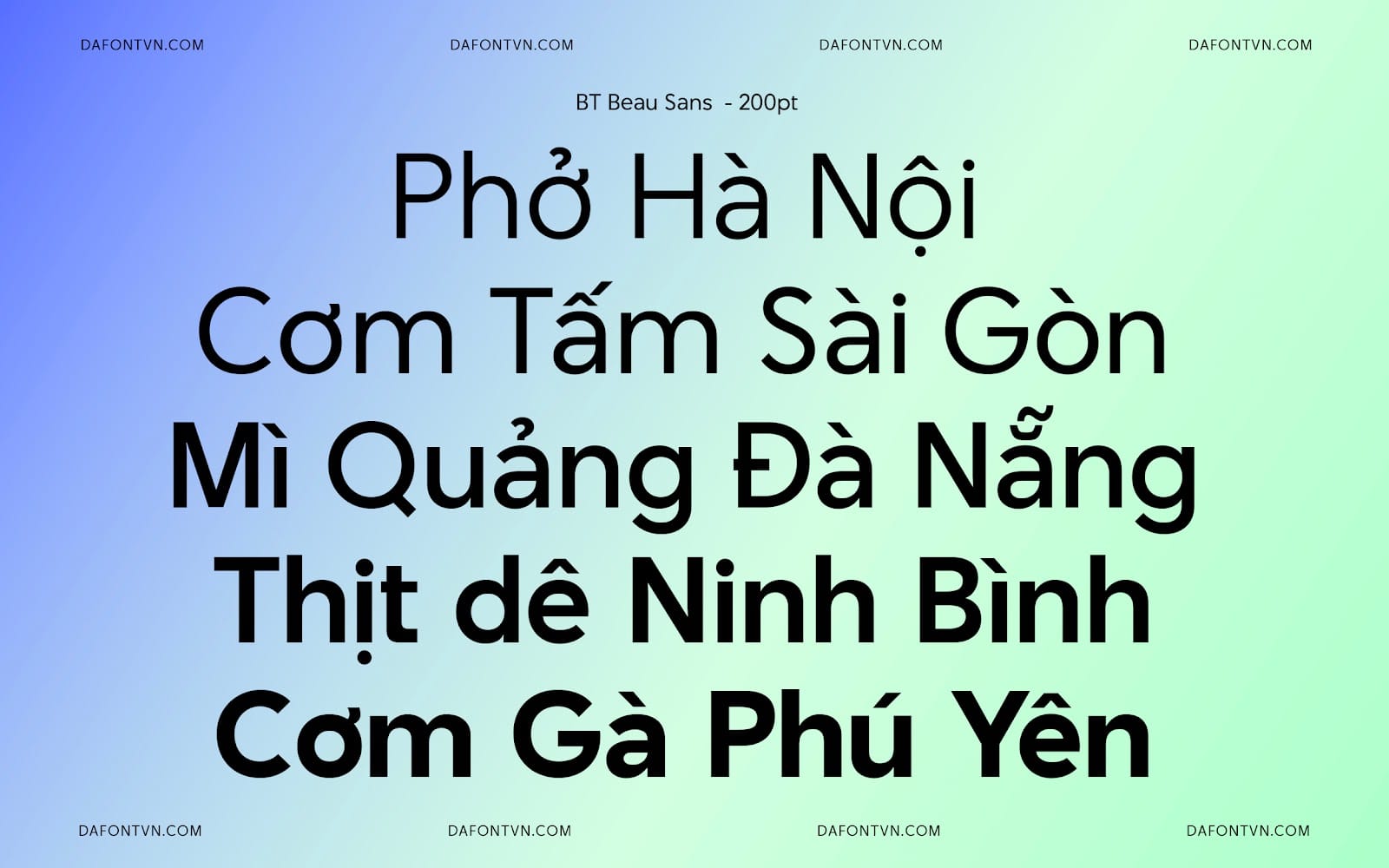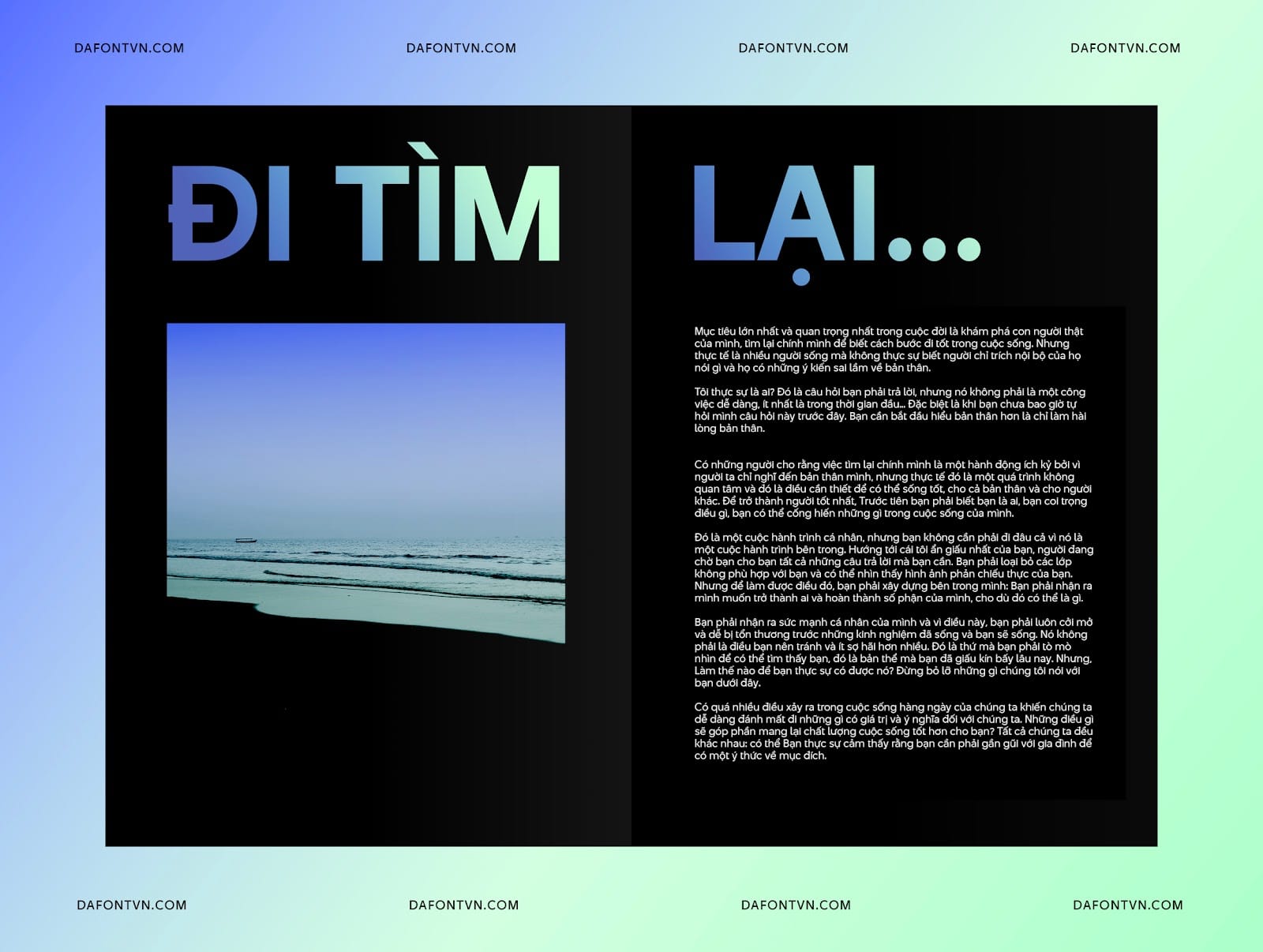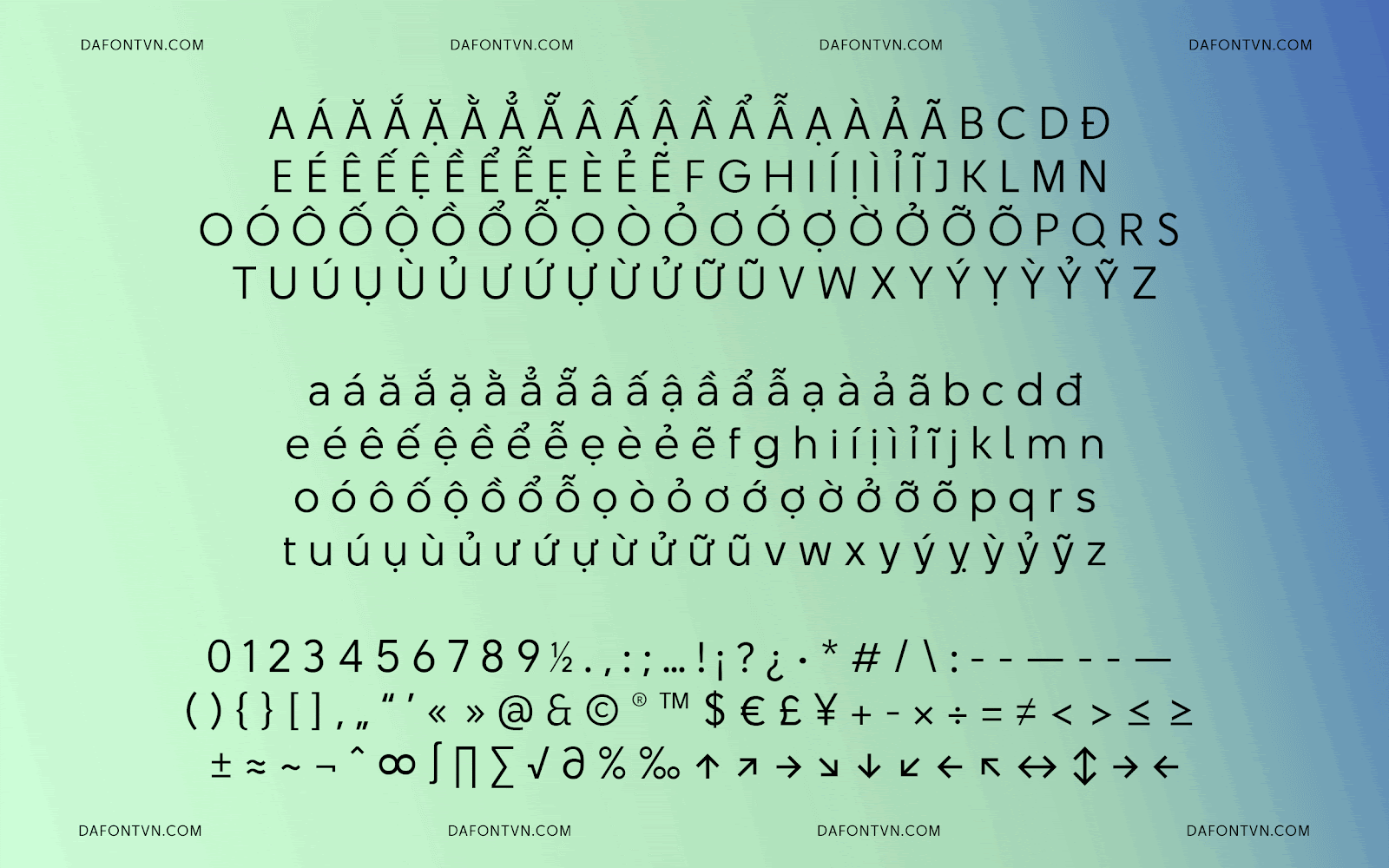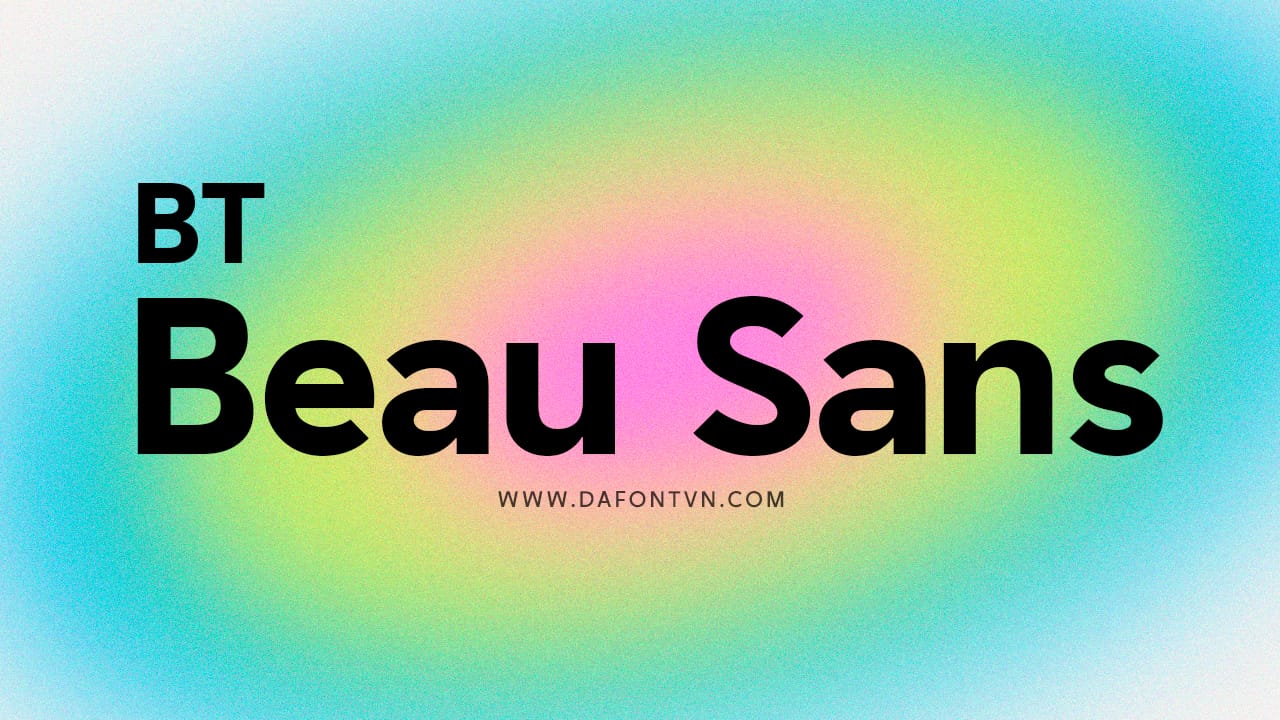
BT Beau Sans là bộ font chữ được thiết kế bởi Beautype Studio được chia sẻ hoàn toàn miễn phí. Font chữ được ra mắt vào năm 2022 lấy cảm hứng từ cuộc sống hàng ngày của chúng ta, khi con người và công nghệ ngày càng hòa nhập, nền tảng digital ăn sâu vào tiềm thức và trở thành một phần không thể thiếu của cuộc sống thường nhật.Từ triết lý thiết kế kể trên, BT Beau Sans được ra đời với những chi tiết đặc thù kiến tạo nên sự khác biệt trong từng con chữ, BT Beau Sans bao gồm 10 kiểu từ Light đến Extra Bold được thiết kế tỉ mỉ mang đến một kiểu chữ hiện đại dễ sử dụng cho bất kỳ thiết kế nào và sử dụng hoàn hảo ở mọi kích thước từ tiêu đề cho đến văn bản.